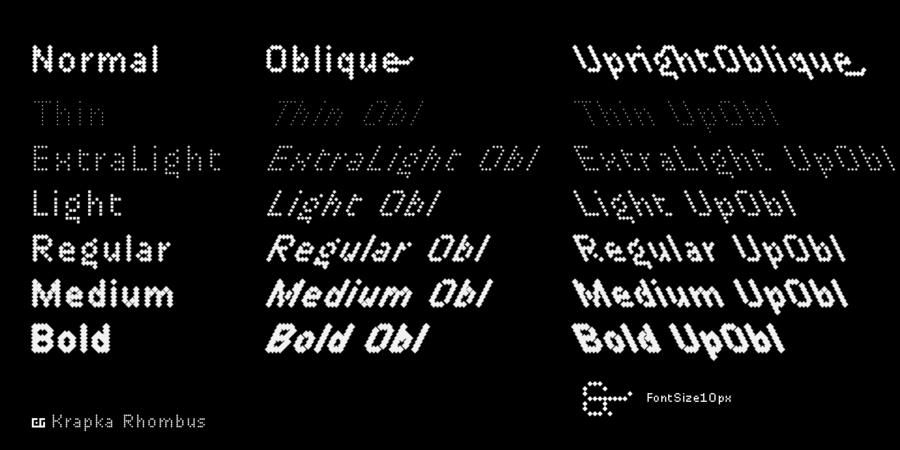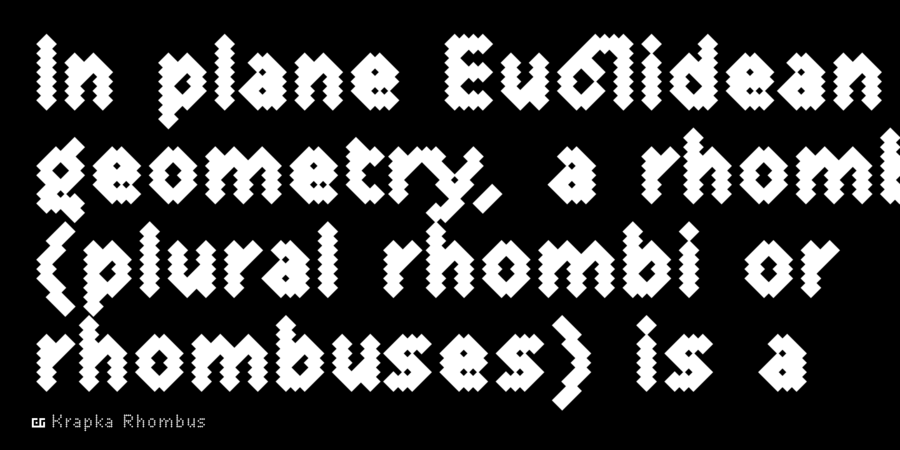
Опис гарнітури DR Krapka RhombusУ цьому шрифтовому сімействі піксель має ромбічну форму. Шрифт підтримує функції OpenType і містить капітель, лігатури, мінускульним цифри, дроби й індекси, історичні форми, стилістичні набори та розчерки. Також присутні символи, стрілки, і навіть емодзі. Для невеликих текстів рекомендується використовувати DR Krapka Rhombus FontSize10px з розміром шрифту рівно 10 пікселів. Сімейство шрифтів DR Krapka Rhombus підтримує європейські мови на основі латинки, кирилицю, в тому числі азіатську, і грецьку абетку. Якщо ви хочете використовувати шрифти з іншою формою пікселів, є й інші сімейства DR Krapka: DR Krapka Square (квадрати), DR Krapka Round (кола). Шрифт розробив Дмитро Растворцев у 2020 році.
Асоціації з сімейством шрифтів DR Krapka RhombusОсобистість і характер гарнітури:
тонкий, легкий, автоматичний, комп'ютерний, електронний, машинний, матричний, інженерний, точний, прозорий, невагомий, байдужий, гострий, різкий, помітний, яскравий, чіткий, психоделічний, значний, впевнений, важкий, дивний, експериментальний, грайливий, робочий, грубий, рівний, логічний, холодний, техногенний, твердий, стійкий, прямокутний, міський, урбаністичний, індустріальний, мужній, армійський, промисловий, незграбний, активний, суворий, брутальний, ігровий, швидкий, строковий, стрімкий, сміливий, рішучий
електроніка, автоматика, код, програмування, інженер, комп'ютер, IT, айтішник, айті, технології, андроїд, фантастика, дискотека, аквадискотека, залізо, гра, наука, робот, математика, хакер, лего, конструктор, цегла, іграшка, мультфільм, дитяча книжка, анімація, екскаватор, урбаністика, інструмент, промисловість, армія, завод, верстат, тара, склад, ремонт, депо, уніформа, вагон, автомат, шутер, екшен, страйкбол, будівництво, будматеріали, бойовик, сталевар, робочий, кубики, графіка, ілюстрація Гарнітура асоціюється з віком: